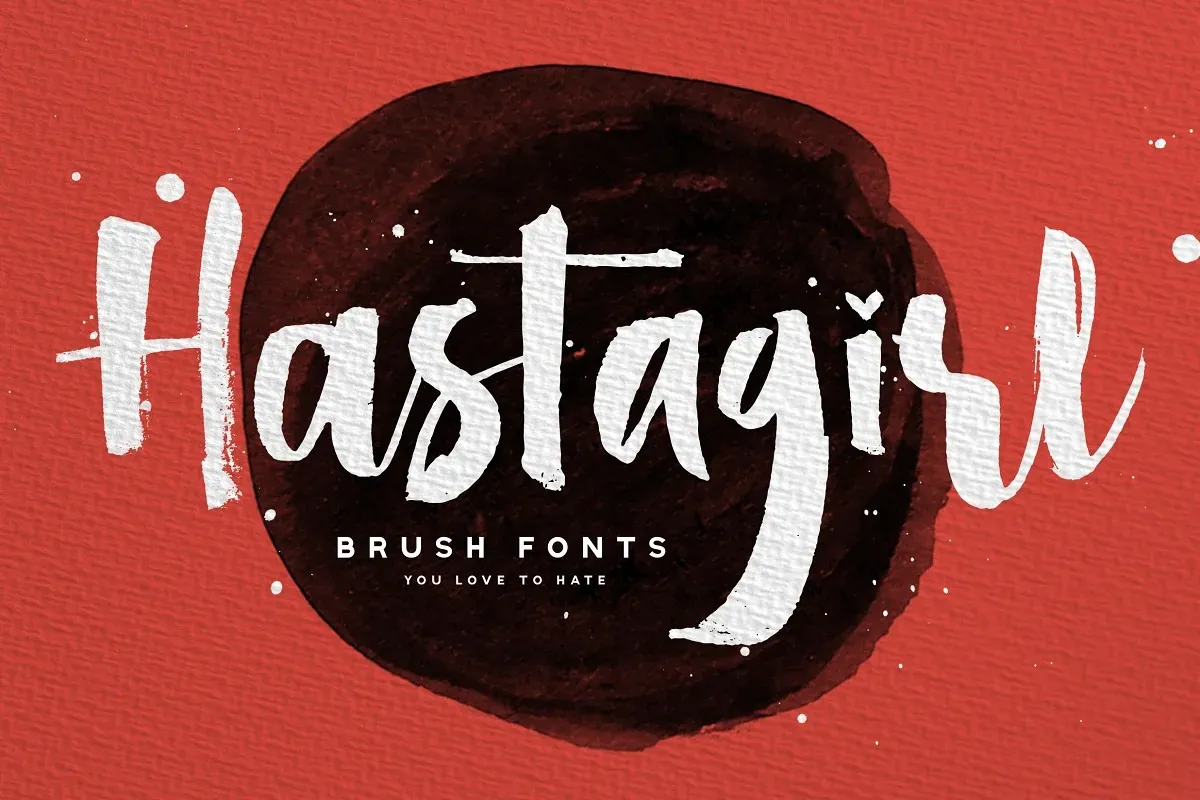
A Hastagirl Font é uma opção única para quem busca um estilo único e autêntico no design. Criada pela Konstantine Studio, esta fonte brush escrita a mão se destaca por seu texto grosso e trabalhado, proporcionando um toque de elegância aos designs mais modernos. Seja para criar uma marca de moda sofisticada ou adicionar um toque criativo às suas postagens nas redes sociais, a Hastagirl é perfeita para incorporar em logotipos de escrita à mão, citações personalizadas, embalagens ou qualquer ocasião que exige um estilo estiloso e dinâmico. Ela se tornará uma aliada valiosa para quem busca expressar individualidade e originalidade em suas criações digitais.